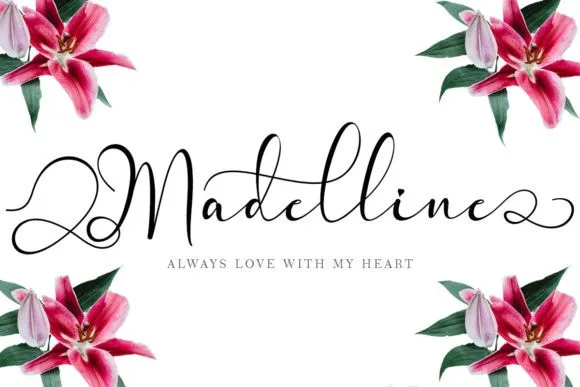
Madelline Calligraphy Font – Download Grátis
Introduzimos a Madelline Calligraphy Font, uma fonte tipográfica script moderna que traz uma mudança muito bonita e elegante ao seu texto. A Madelline é decorada com um toque de cobiça clássico, mas também tem uma pitada de modernidade, resultando em um design detalhado que transmite um estilo elegante. Foi criada pela yogaletter6. Esta fonte Madelline possui um ar romântico e elegante, perfeita para decorar qualquer tipo de trabalho. É o tipo de fonte que pode tornar seu trabalho ainda mais bonito e sofisticado. Seja você um designer gráfico ou criador de conteúdo, a Madelline está aqui para enriquecer sua biblioteca de fontes. Seu design vem diretamente da plataforma de design 99designs, onde yogaletter6 compartilhou essa fonte com o mundo. Um leque de escolha semelhante, mas certamente não tão exuberante quanto a Madelline Calligraphy Font.